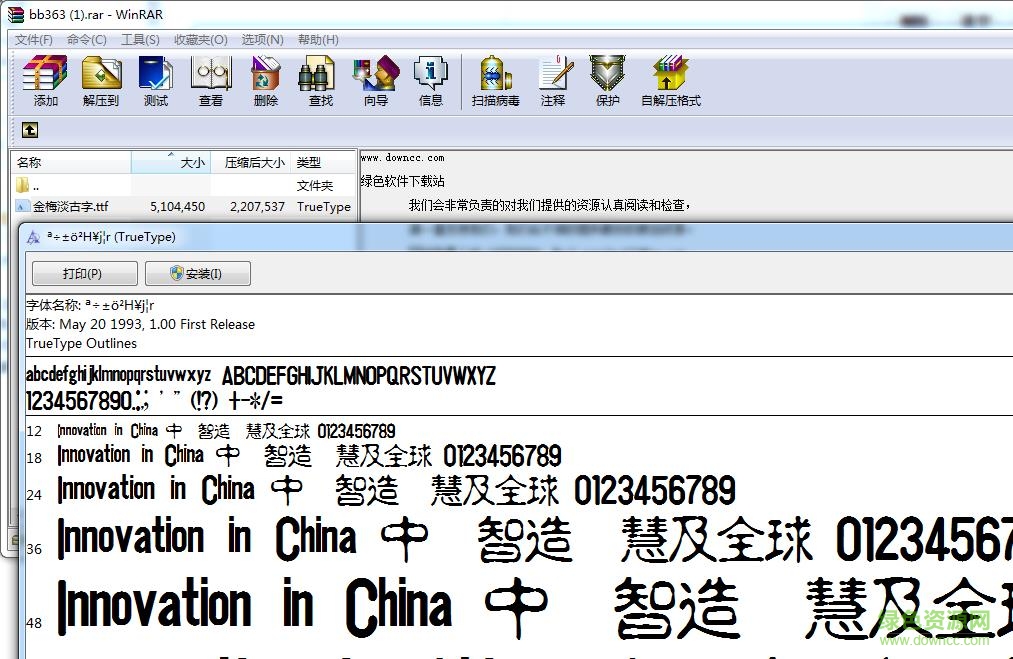
金梅淡古字字體是一款非常具有古風氣息的中文藝術字體,這款字體看上去十分美觀,適用于多種不同領域使用,有需要的用戶趕快來本站免費下載體驗吧!
金梅淡古字即古代書法字體,讓你感覺到獨特的古風韻味,能夠融合到古風創(chuàng)作的圖片中進行題詞等創(chuàng)作,能夠帶給你觀看著們不錯的視覺體驗,同時其能夠運用到眾多的生活創(chuàng)作于工作創(chuàng)作中!